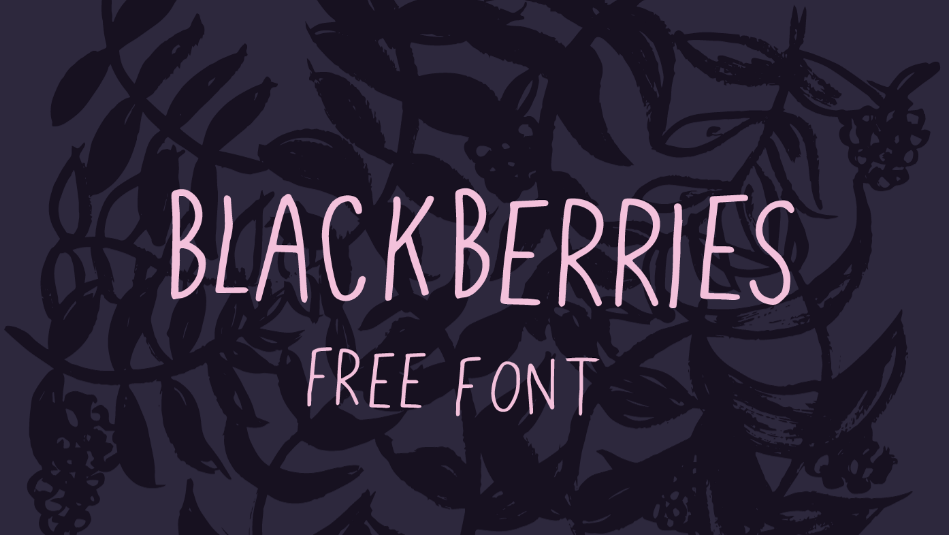
Blackberries- A sweet Font – Download Grátis
A Blackberries é uma fonte elegante que evoca a frescura dos vermelhos intensos das blackberries maduras. Inspirada no traço livre, essa fonte foi originalmente escrita à mão e agora está disponível para uso pessoal gratuitamente. Com dois pesos de grau variável, Blackberries oferece um toque de sutileza que combina perfeitamente com textos mais informais ou artísticos. Sua simplicidade e elegância fazem-a uma escolha perfeita para qualquer projeto que deseje dar um toque natural e autêntico. Se você se identifica com essa fonte, não hesite em experimentar seu poderoso traço às suas próximas criações digitais. Além disso, há a opção de adquirir uma licença comercial através da Behance ou por meio do contato direto. Estamos entusiasmados em conhecê-lo e deixaremos um espaço para que você compartilhe seus pensamentos sobre essa fonte no futuro.